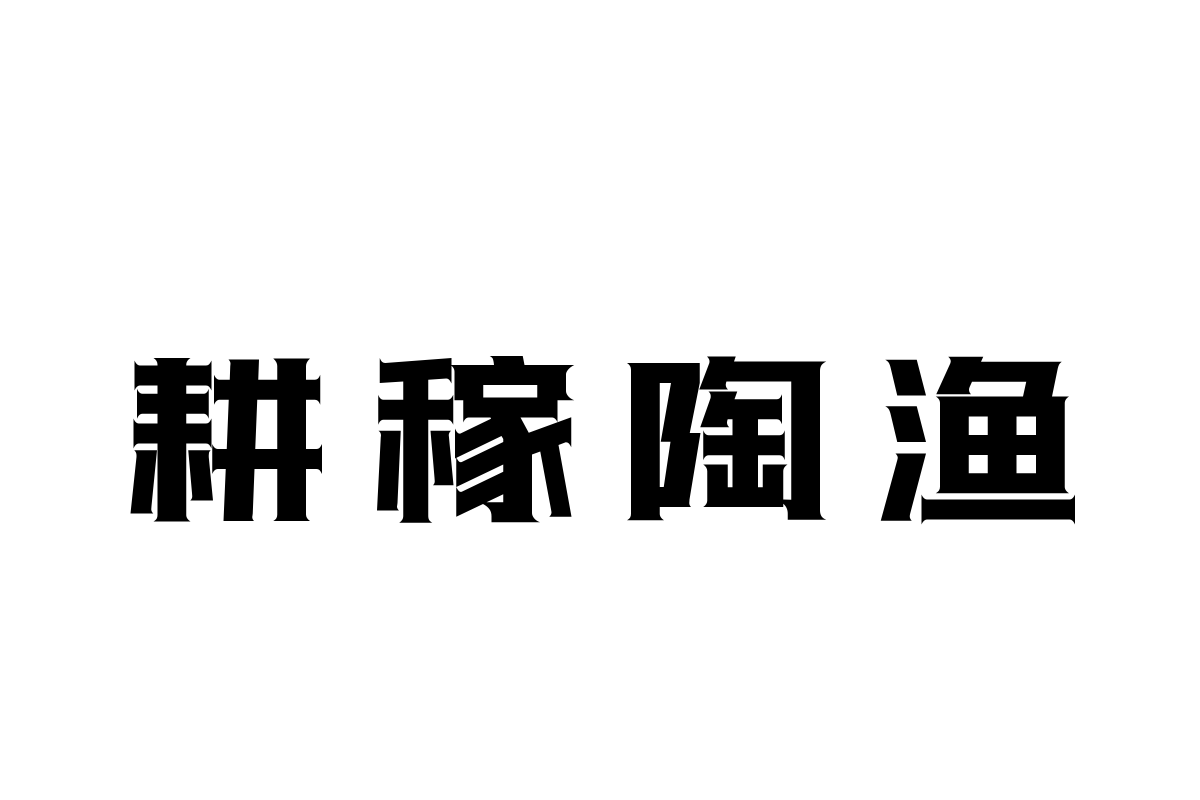
三极光耀简体W4是一款中文字体,由北京华文联创科技有限公司设计。这款字体以其独特的设计风格和丰富的表现力受到了广泛的欢迎。
三极光耀简体W4的设计理念是简洁、现代,旨在为用户提供一种清晰、易读的文字体验。它采用了无衬线的设计元素,使得文字更加清晰易读,同时也保留了一定的艺术感。在字形方面,三极光耀简体W4采用了简洁的线条和结构,使得文字看起来更加优雅、大方。
此外,三极光耀简体W4还具有较强的可扩展性,可以用于各种类型的文本,包括标题、正文、广告等。它的使用范围广泛,无论是在网页、印刷品还是电子屏幕上都可以得到很好的效果。
总的来说,三极光耀简体W4是一款非常实用的中文字体,适合用于需要清晰、易读的文字展示场合。